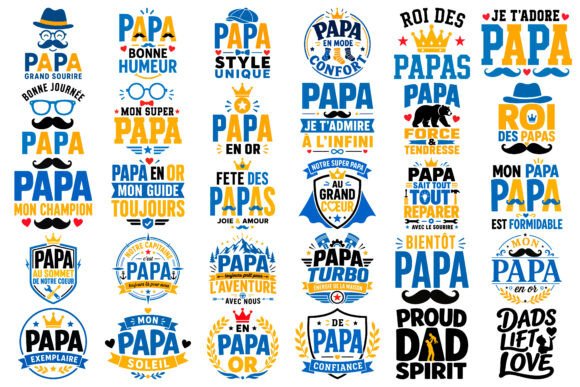
Multilingual Papa Typography Vector Bund
Trouver les bons éléments de conception peut être un défi, mais Multilingual Papa Typography Vector Bund propose une collection exceptionnelle qui rehausse instantanément votre travail.
Conçu avec précision, Multilingual Papa Typography Vector Bund offre des vecteurs nets, une typographie fluide et une licence commerciale pour une tranquillité d'esprit.